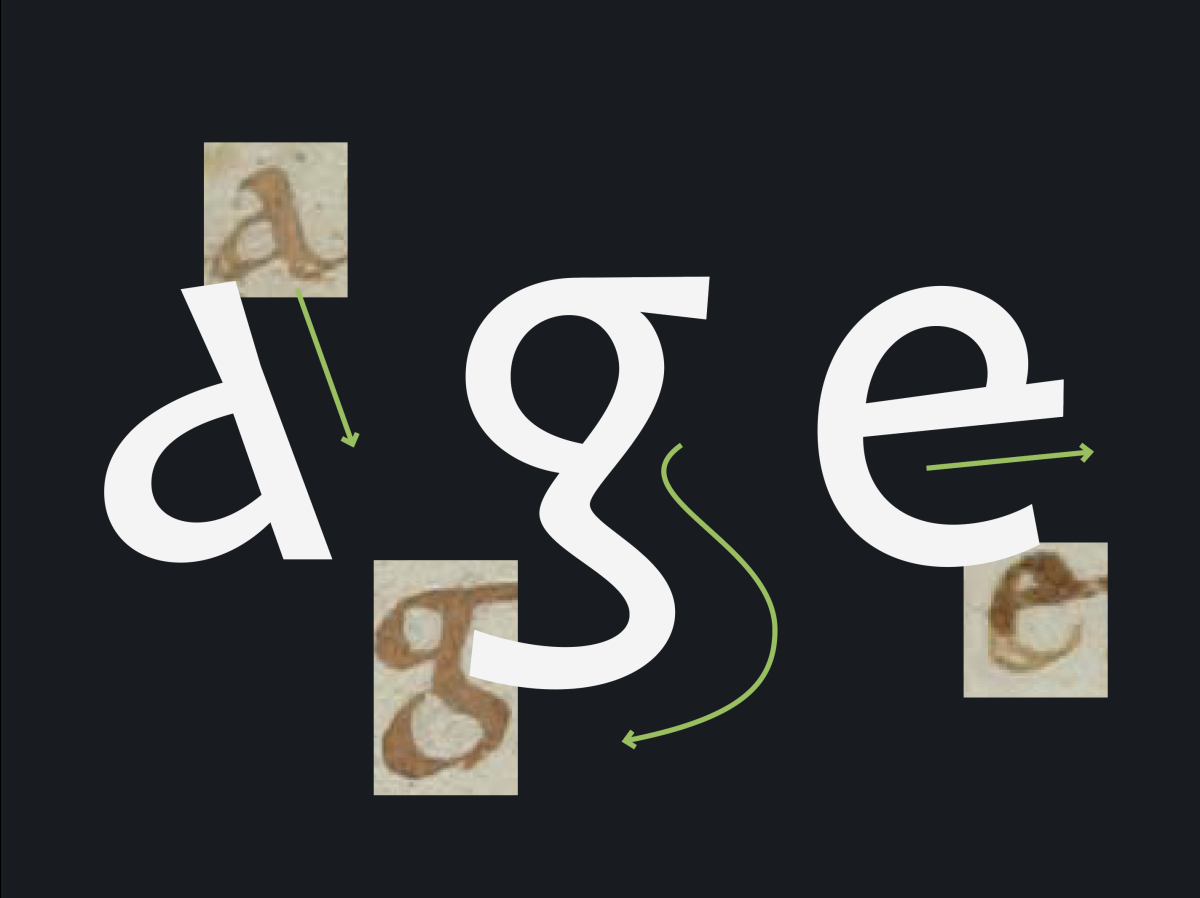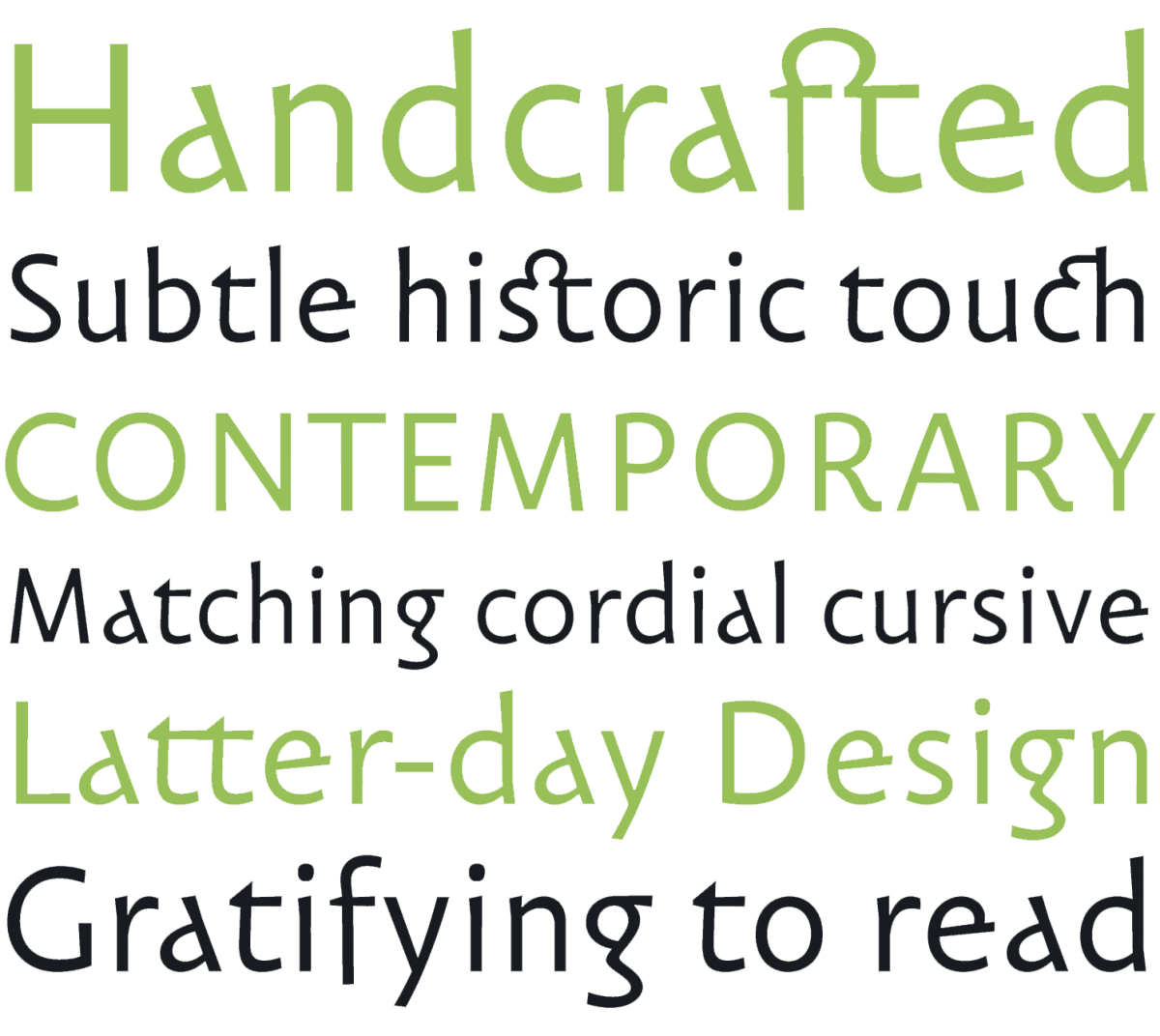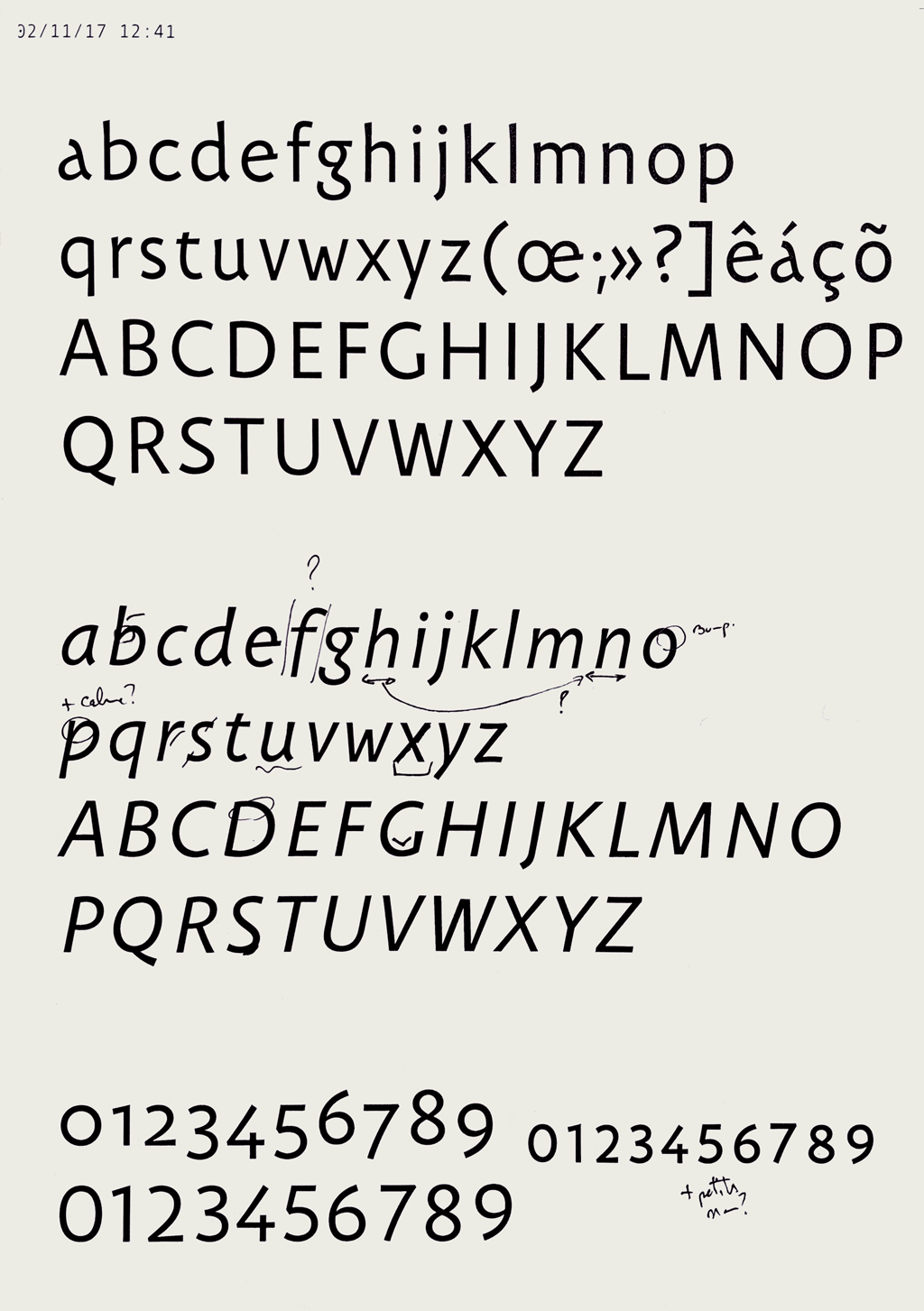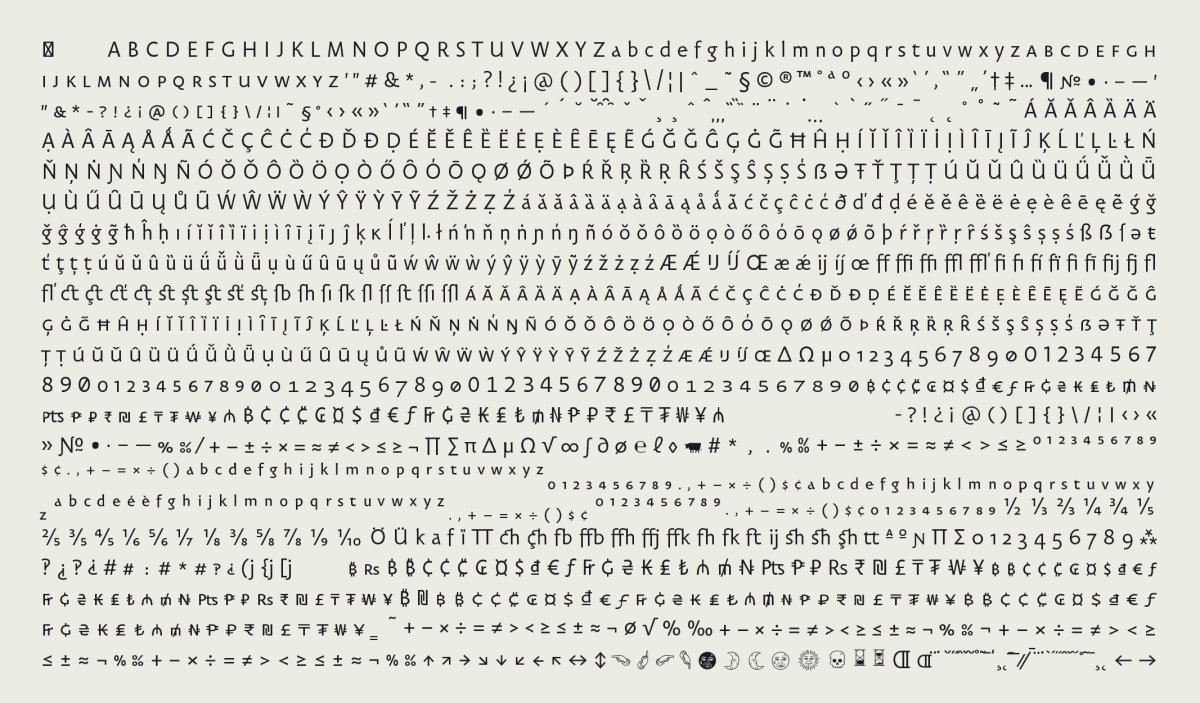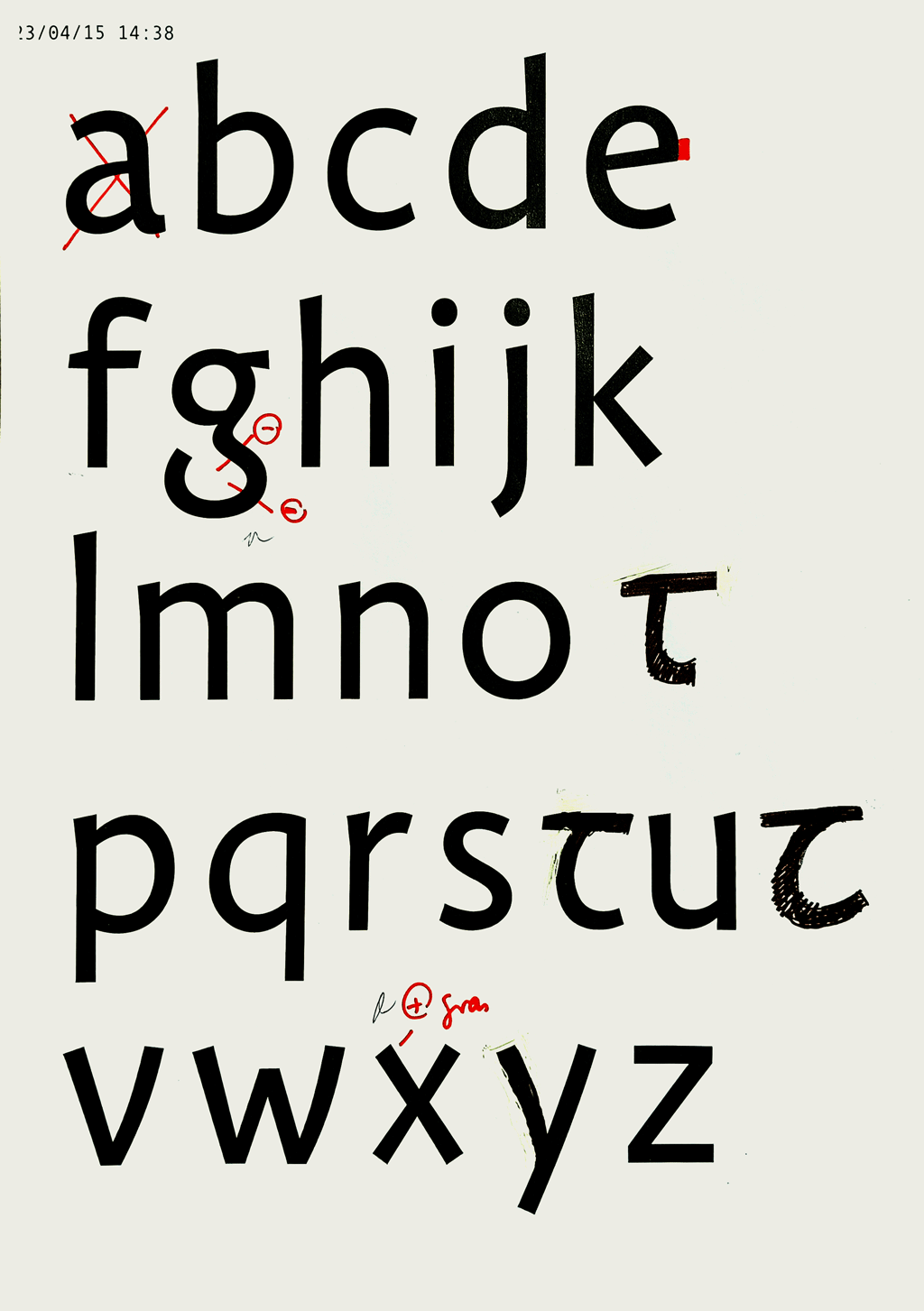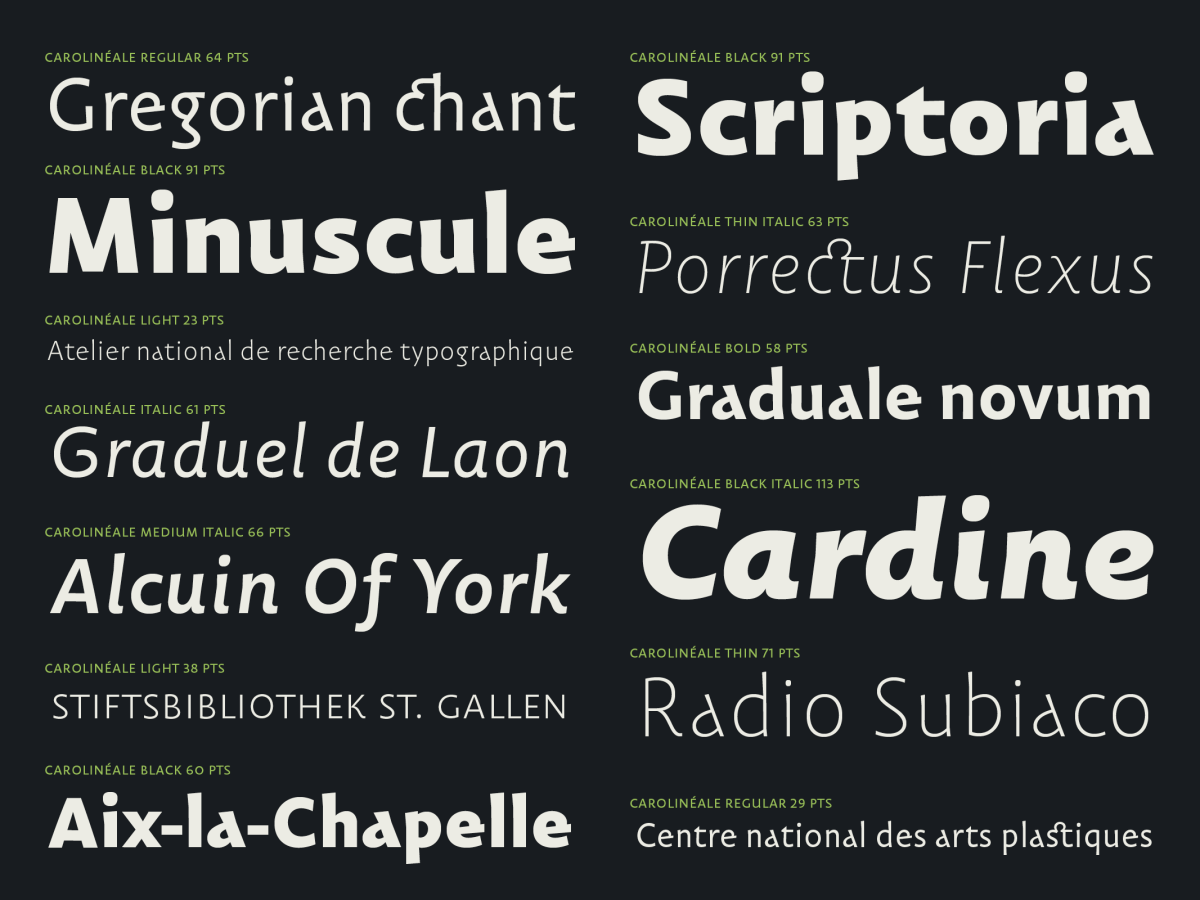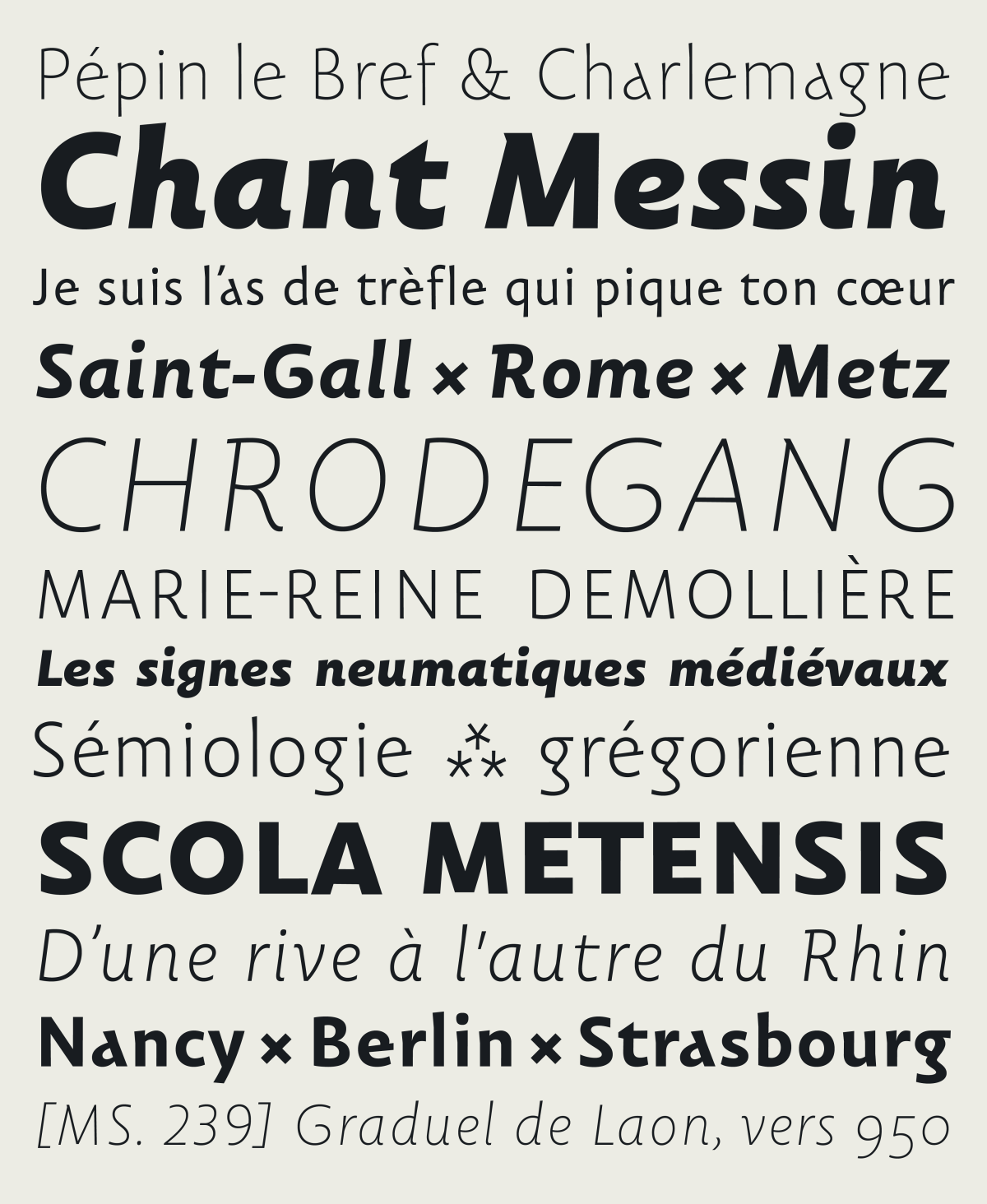
Le dessin de Carolinéale, une sans serif humaniste inspirée des livres de chants médiévaux
Carolinéale est une famille de caractères dont j’ai entamé le dessin fin 2014, lorsque j’intégrais l’Atelier National de Recherche Typographique, à Nancy (FR). J’avais alors le projet de travailler sur une version typographique des notations musicales carolingiennes. Le caractère alphabétique associé à ce travail a bien évolué depuis. J’ai pu, notamment grâce au soutien du Centre National des Arts plastiques (FR) et au regard aiguisé d’Alejandro Lo Celso, en faire émerger une famille de caractère complète. À l’occasion de sa publication chez PampaType, j’aimerais revenir ici sur les principes qui ont guidé le dessin de ses formes.
Une source
Les manuscrits carolingiens de chant Grégorien présentent sur leurs pages des signes mystérieux, inscrits au-dessus du texte latin. Ce sont les premières formes de notation de la mélodie. Ces signes plus que millénaires — qu'on appelle des neumes — sont encore utilisés de nos jours. Leur composition assistée par ordinateur relève du véritable défi typographique, nos outils numériques n’étant pas du tout adaptés à ce type d’inscription. En entamant mon post-Master à l’ANRT, j’avais pour projet de trouver une solution typographique permettant de résoudre cette situation avec élégance et cohérence.
Une double page du manuscrit MS. 239, dit “Graduel de Laon”, copié vers 950. Texte en latin [minuscule caroline] et notation mélodique en neumes dits “Messins”.
Je proposais alors une interprétation typographique plus contemporaine des signes musicaux (plus précisément des signes dit de « Metz » et de « Saint-Gall »), inspirée par le tracé carolingien, mais aussi par leur version actuelle, tracée le plus souvent au feutre ou au stylo-bille. Je numérisais ensuite le tout, intégrais la chose à un fichier typographique respectant une nomenclature précise, afin de pouvoir composer avec le caractère dans un logiciel dédié à la gravure de partitions : Grégorio 1.
À gauche: quelques signes musicaux conçus à l'ANRT en 2015 [système de notation de St-Gall]. À droite: Les signes carolingiens tracés par un outil contemporain: un tableau blanc utilisé lors d'un stage de chant Grégorien, Metz.
Dans le même mouvement, je décidais d’accompagner les neumes d’un caractère alphabétique basé sur des principes similaires : structure historique, approche monolinéaire. À la fois une minuscule caroline et une linéale ; c’était la naissance de Carolinéale. 2
Une écriture
Le texte des manuscrits de chant du IXe siècle est écrit dans une forme remarquable. La calligraphie employée est relativement récente pour l’époque. On l’appelle « minuscule caroline », puisque c’est Charlemagne qui en est à l’initiative.
Page du Versicularium, Hymnary, Tropary, Sequentiary, copiée vers 930, St. Gallen, Stiftsbibliothek, Cod. Sang. 381.
Développée lentement, la minuscule caroline ne trouve sa stabilité qu’au IXe siècle, se débarrassant petit à petit de la présence de caractères mérovingiens. Avec l’essor des scriptoria carolingiens, l’écriture améliore sa lisibilité et se répand au-delà des frontières de l’empire. L’origine calligraphique de cette forme scripturale puise ses sources dans les écritures onciales et semi-onciales qui la précèdent.
La minuscule caroline à son apogée est accompagnée alternativement de capitales romaines, capitales rustica et de lettres onciales. Le point est parfois placé à mi-hauteur d’x, on ne trouve pas de point sur le i, mais sont intégrés le point d’interrogation, les guillemets et la virgule. À gauche: folio 438 de la Bible Granval, copiée dans l'abbaye de Saint-Martin de Tours entre 825 et 850. Image prise de Claude Mediavilla, Caligrafía, Campgràfic, Valencia 2005 [p.141].
Un romain
Carolinéale Romain s’appuie sur les formes les plus symptomatiques de la minuscule Carolingienne. Plus précisément, le caractère se base sur l’écriture des manuscrits des scriptoria du bassin rhénan, produits entre le IXe et le Xe siècle.
Premières esquisses numériques : Avril 2015 - ANRT, Nancy.
Mise au point de l'italique, Saint-Gall, novembre 2017.
J’ai essayé d‘en proposer une interprétation monolinéaire et subjective, qui cherche à en garder l’ADN, tout en restant la plus stable, lisible et contemporaine possible. Les glyphes de Carolinéale ont tous dans leurs constructions une trace plus ou moins présente d‘une origine dessinée. Chaque signe cherche à trouver un point d’équilibre satisfaisant, quelque part entre le vocabulaire d’une linéale contemporaine et celui de la calligraphie médiévale.
Carolinéale Regular avec quelques ligatures.
Quelques caractéristiques fortes du dessin carolingien ont été conservées. On notera par exemple l’angle diagonal très marqué du  a, ainsi qu’un arrêt net de son dessin à hauteur d’x. Le  g reste également médiéval dans sa construction, en se déployant « à contresens » d’un g binoculaire moderne, dans sa partie inférieure. Enfin, on remarquera également que le e conserve une traverse débordante, un trait de plume souvent absent des linéales.
2. Je dois ce nom a Gerard Unger, type-designer néerlandais de renom, qui me l’aura glissé alors qu’il assistait à ma présentation de fin de post-Master à l’ANRT.
3. Le concept est purement typographique et a été introduit à la fin du 15e siècle par Francesco Griffo da Bologna.
4. On pense notamment au travail de Frederic W. Goudy sur sa Goudy Sans.